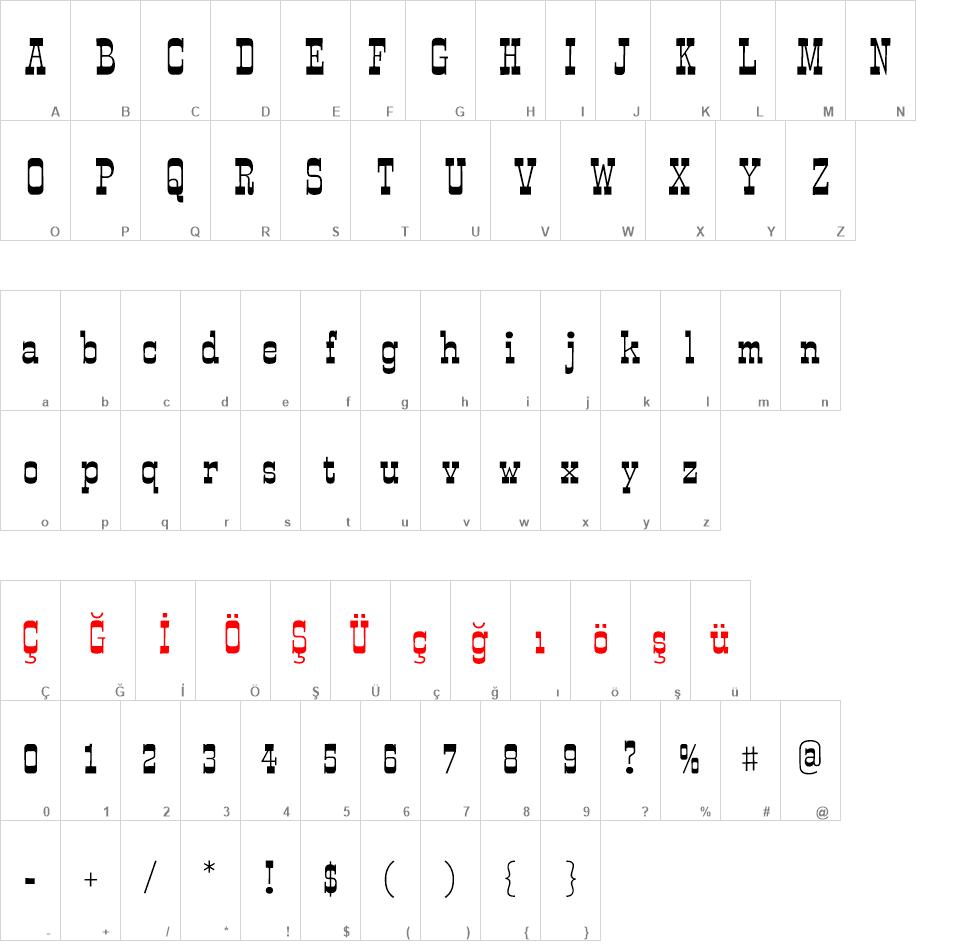
Smokum
Smokum font
Tuxedo ist eine vom Westen inspirierte Slab-Serif-Schriftart, die ein wenig Spaß macht. Ein wenig lockeres Land eignet sich hervorragend für die Verwendung von Überschriften und Bildschirmanwendungen, die Eleganz erfordern, aber aufgrund des Kontrasts von Dicken und Verdünnungsmitteln erzielt es die beste Leistung als WebFont in mittleren und großen Punktgrößen.